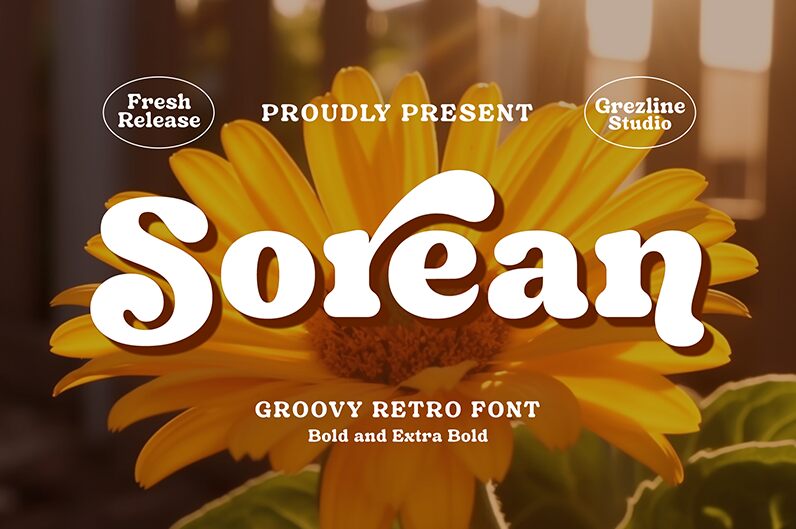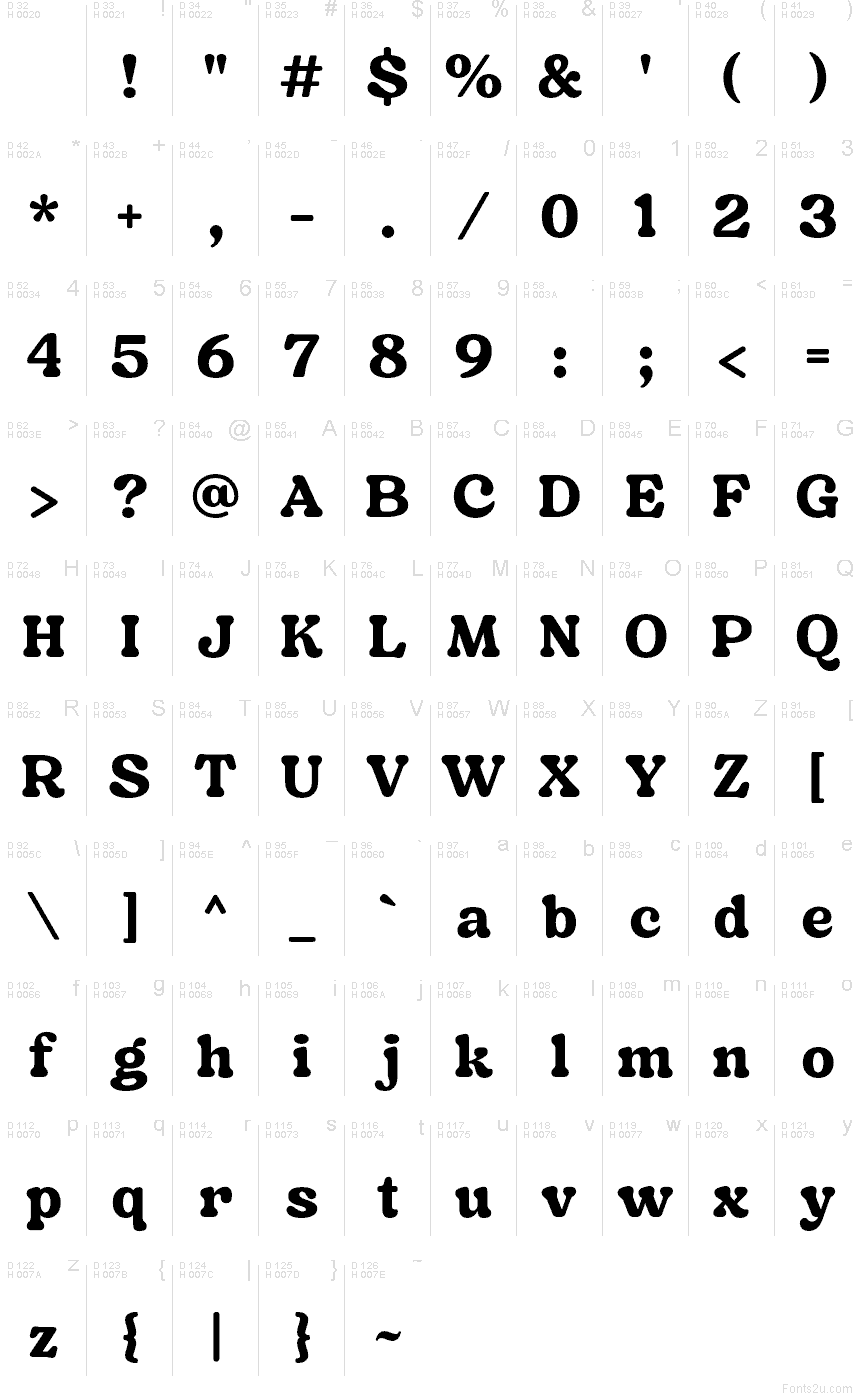
Sorean Bold od Akhmada Rezu Fauziho je bezplatné retro display písmo so širokými, ťažkými literami a jemne zaoblenými egyptskými pätkami. Jeho plné krivky a zúžené spoje ťahov pripomínajú hravé nápisy zo 70. rokov, no tvary zostávajú pevné a nerozpadávajú sa.
Obal vinylovej platne je mimoriadne presvedčivým prostredím pre jeho hrejivé, naddimenzované proporcie. Rovnaký vintage náboj pristane kaviarenským baleniam, festivalovým plagátom aj grafike na neformálnom oblečení. Vo všetkých týchto použitiach zaoblená masívnosť spája nostalgické motívy s uvoľneným grafickým spracovaním.